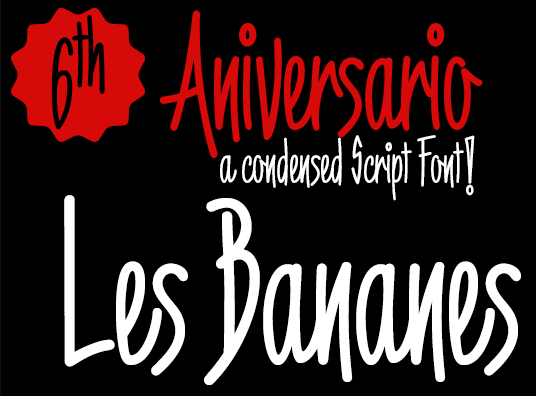
A Font ‘6th Aniversario’ é uma opção perfeita para designers que buscam elegância e eficiência no design visual. Sua tipografia redonda, condensada e escrita a mão se destaca por sua facilidade de leitura e economia de espaço, tornando-a ideal para títulos publicitários em posteres, flyers ou qualquer outro tipo de publicação onde o uso de recursos limitados é essencial. Além disso, inclui um símbolo do Bitcoin como uma ligatura especial. O design elegante desta font se encaixa perfeitamente com a necessidade de economia de espaço e boa legibilidade que as aplicações gráficas modernas exigem. O uso de letras redondas e condensadas permite criar títulos poderosos, mesmo em espaços muito reduzidos, o que torna ‘6th Aniversario’ uma escolha atraente para designers interessados em destacar seu trabalho no design publicitário ou editorial. O Bitcoin símbolo, presente como uma ligação especial na fonte, adiciona um toque de modernidade e relevância à ‘6th Aniversario’, tornando-a ainda mais versátil para aplicações que precisam combinar elegância com tecnologia atual. Esta font é especialmente indicada para designers que buscam a harmonia entre o estilismo tradicional da escrita a mão e as tendências atuais da criptomoeda, oferecendo uma solução de design multifuncional e moderna.